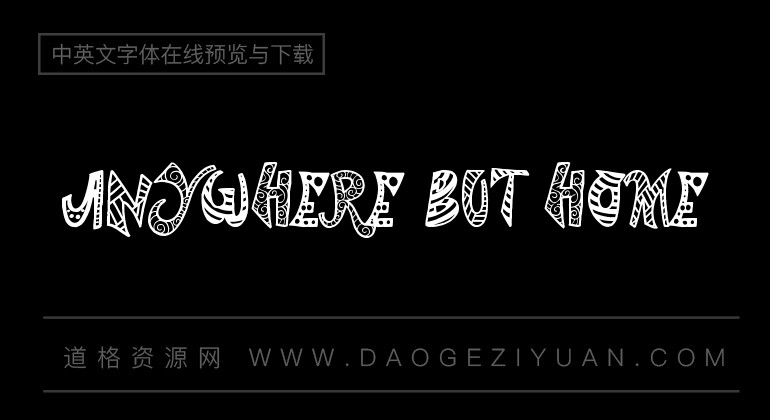
Anywhere But Home是一款抒情体的字体,它具有温暖、舒适的感觉,给人一种放松的感觉。它的字体特点是比较轻松,给人以安全感,可以在多种背景下使用,支持多种语言,可以用于各种印刷品,网页、广告等。它也可以用于设计标识、标题、封面、图片和文字等。内容介绍
Anywhere But Home是一款非常不错的手写艺术字体,具有很好的视觉感,适合于文化类的宣传设计、商业类品牌的广告和产品包装设计以及个性化文字排版等较多场景。